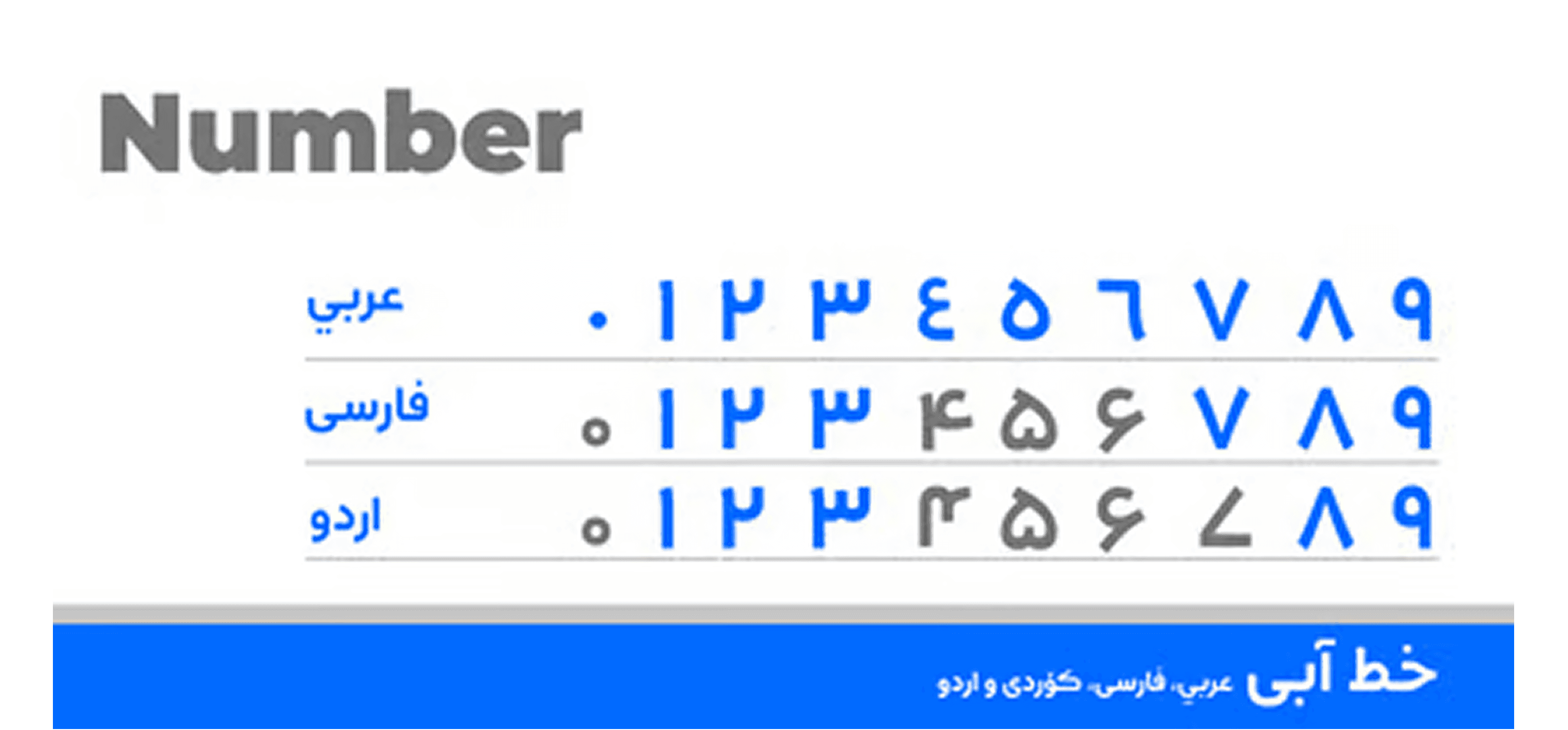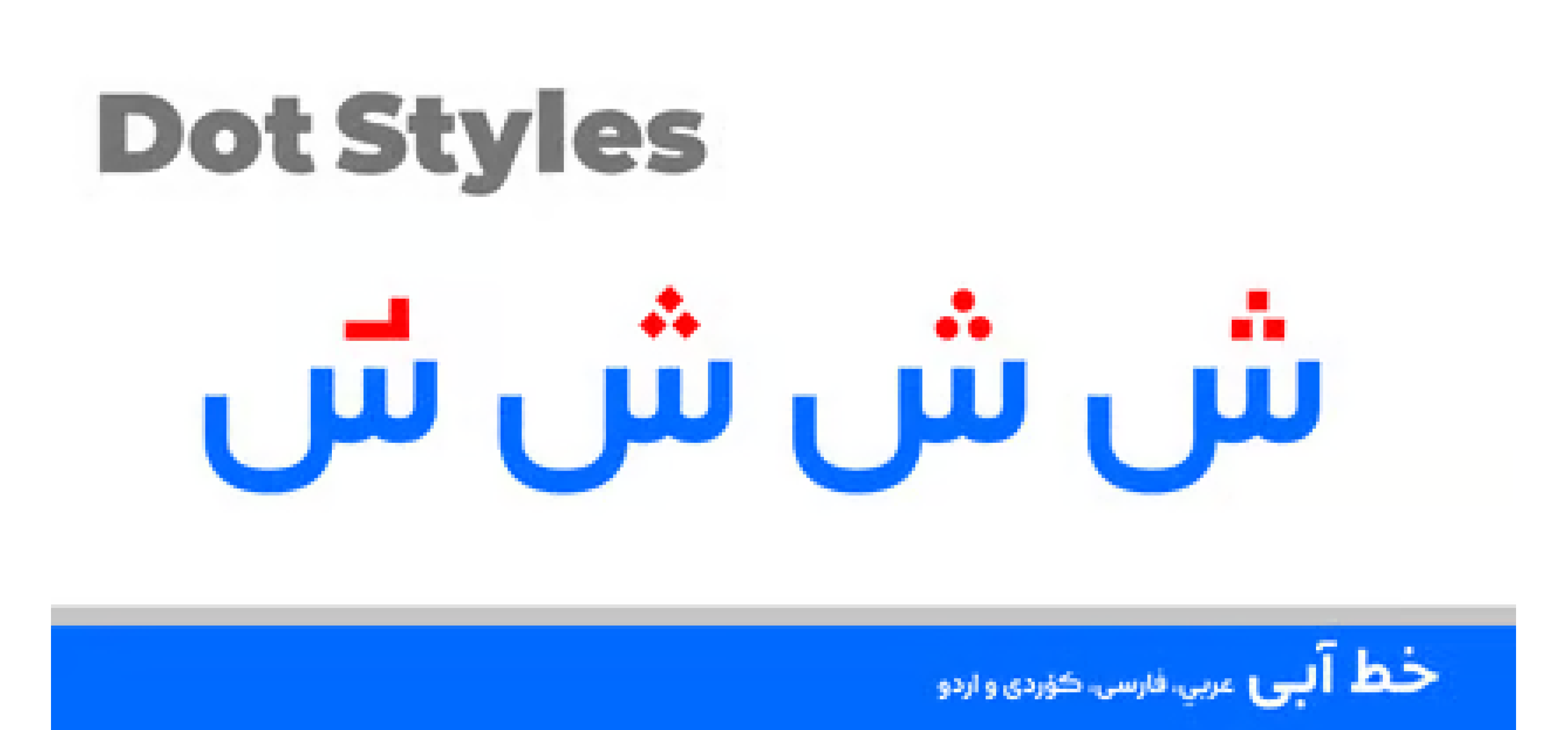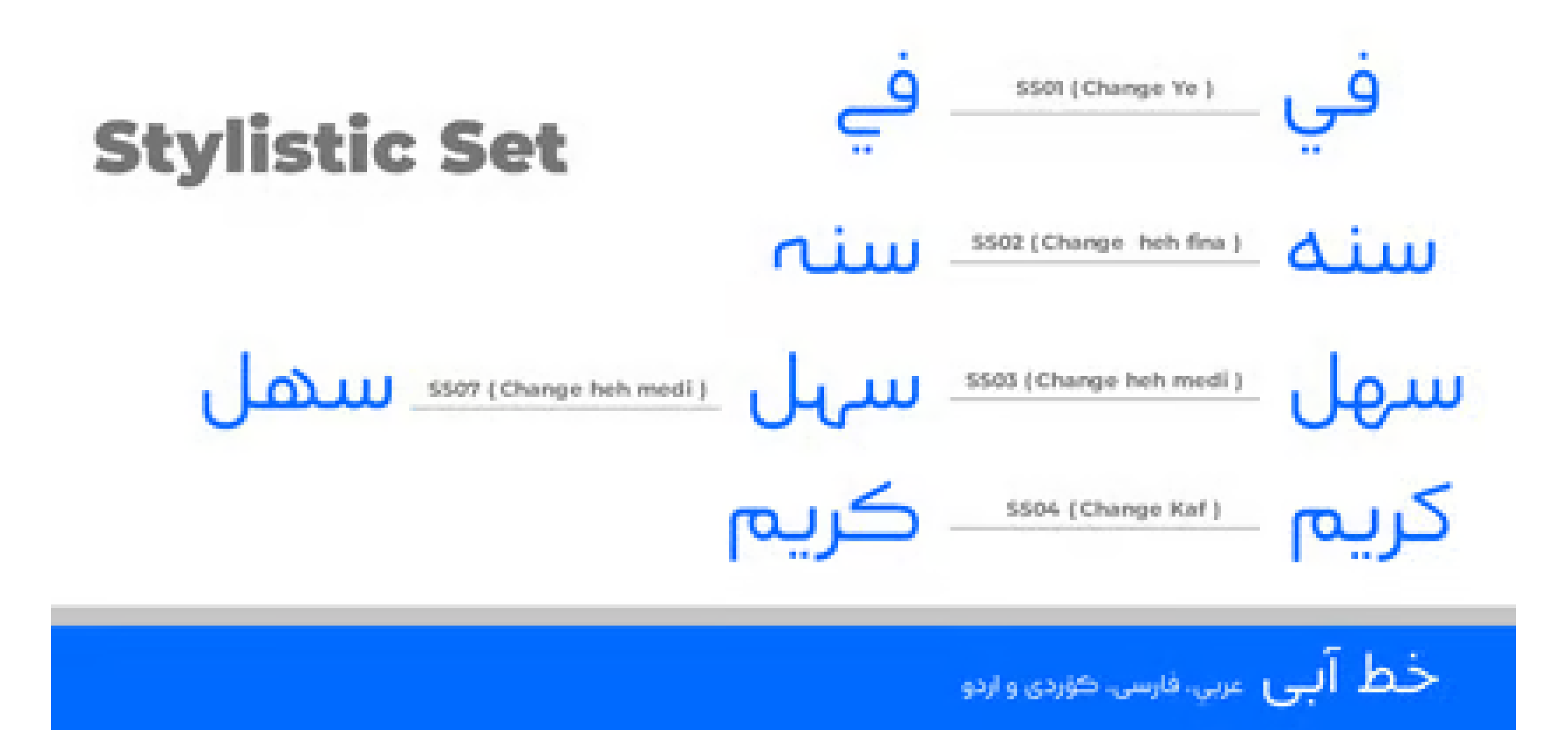
الخط "آبي" يتوفر بـ10 أوزان مختلفة وبصيغ متعددة مثل TTF وWeb، بالإضافة إلى ملف منفصل للنسخة المتغيرة (VF)، مما يجعله اختيارًا مناسبًا للعملاء الكرام. من أبرز خصائص هذا الخط هو حفاظه على البساطة والنقاء، دون الانشغال بالتفاصيل المعقدة.